A 90 años de la publicación de su libro Die neue typographie
El alemán Jan Tschichold es uno de los principales referentes del diseño tipográfico. Publicado hace 90 años, su libro Die neue Typographie (La nueva tipografía) es una de las obras más influyentes en la definición de las nociones de tipografía moderna.
Tschichold nació en la ciudad de Leipzig en 1902, hijo de un rotulista y pintor de letreros. Aprendió caligrafía, grabado y encuadernación, y pasó por la Academia de Artes Gráficas, donde se familiarizó con las nociones de diseño clásicas. Sin embargo, fueron las vanguardias de la década de los años 20 las que llamaron su atención.
Atraído por movimientos como el suprematismo y el constructivismo, su asistencia a la primera exposición de la Bauhaus en Weimar le permitió consolidar una nueva forma de entender la tipografía, alejada del estilo tradicional.
Influenciado por el clima de la época, en 1925 publicó un manifiesto llamado Tipografía Elemental, en la revista Typographische Mitteilungen, en el que estableció algunos principios que serían el antecedente de su obra más reconocida. Entre ellos se destacaban la concepción de la tipografía de acuerdo a la función y la idea de la comunicación como objetivo central.
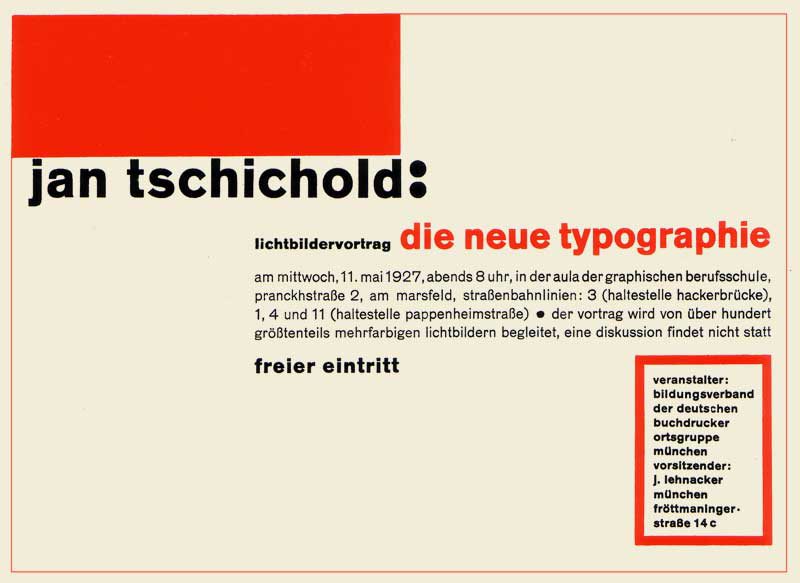
Die neue typographie
Publicada por primera vez en 1928, La nueva tipografía, se editó inicialmente solo en alemán. Impresa en A5, llevaba un encuadernado negro, donde solo el título figuraba en plateado sobre el lomo.
Concebida para profesionales, en sus páginas sentó las bases de un nuevo sistema de composición, que abriría el camino para el diseño de la tipografía moderna, al mismo tiempo que relevaba y manifestaba su compromiso con el trabajo realizado por las vanguardias.
Editada en caja baja y con una preponderancia de minúsculas, la obra de Tschichold defiende el uso de la fuente sans serif por sobre la serif, además de hacer prevalecer los diagramas asimétricos frente a los simétricos, con el objetivo de generar ritmo y tensión en la estructuración de una página.
Por otro lado, identifica a la fotografía como un elemento complementario al texto, en lugar de solo ilustrativo, y valoriza los espacios en blanco, en comparación a la reducción de márgenes propuesta por el enfoque tradicional. A su vez, apunta al diseño no centralizado y establece el uso de diferentes tamaños y grosores tipográficos como recursos para transmitir información de manera simple y rápida.
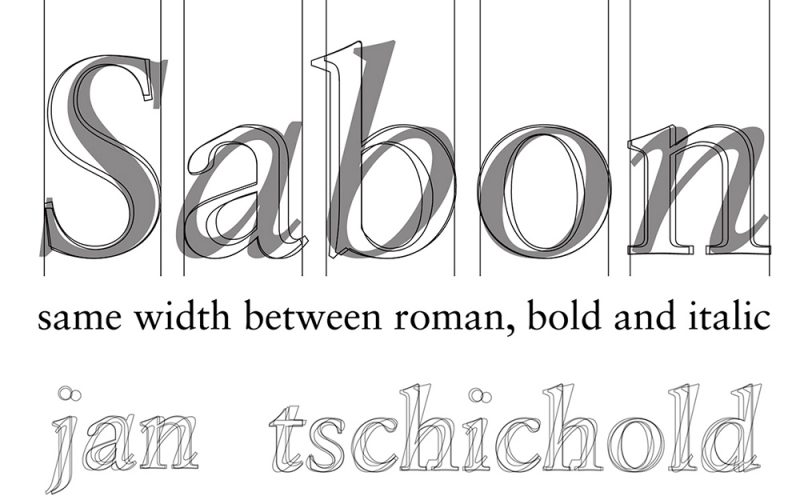
Sus años fuera de Alemania
En 1933, la llegada de Hitler al poder repercutirá en la carrera de Tschichold. Sospechado por colaboracionista con el comunismo, se exilió en Suiza, donde se enfocó en nuevas publicaciones y en el trabajo editorial.
Sus diseños interesaron a los responsables de la firma inglesa Penguin, quienes le propusieron rediseñar su colección de títulos, encargo que el alemán aceptó en 1947. Para ejecutarlo, definió previamente las Penguin Composition Rules, una serie de reglas consideradas como el primer manual de estilo editorial, en donde establecía los márgenes, títulos, adornos y símbolos que aparecerían en los libros, con el fin de facilitar la comunicación entre el autor y el lector.
Su carrera encontró un nuevo hito en 1960, cuando la compañía Linotype le pidió crear una nueva tipografía que pudiera utilizarse tanto en monotipia como en linotipia, y que fuera similar a la Monotype Garamond, proyecto que dio como resultado a la letra Sabon.
Tras una prolífica obra, y a 90 años de la publicación de su libro más popular, el trabajo de Jan Tschichold continúa tan vigente como el primer día. Los principios establecidos en sus páginas fueron fundamentales para el desarrollo del diseño tipográfico durante todo el siglo XX.